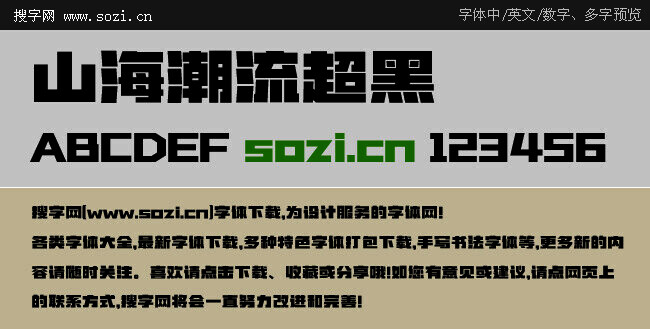
山海潮流超黑
搜字網(wǎng)提供一款山海潮流超黑中文藝術(shù)字體下載,該字體是一款具有強(qiáng)勁視覺沖擊力的綜藝風(fēng)格標(biāo)題字體。字形寬大扁平,充實(shí)填滿整個字框,造型硬朗,全直線的筆畫構(gòu)成棱角分明、堅實(shí)有力。適合包裝設(shè)計、海報設(shè)計、廣告設(shè)計等應(yīng)用。
• 風(fēng)格類別: 海報POP體